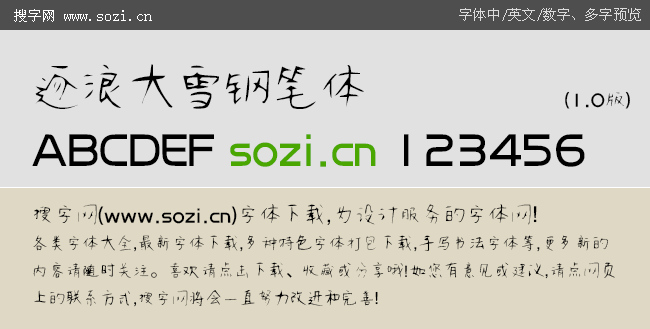
逐浪大雪鋼筆體
搜字網(wǎng)提供一款逐浪大雪鋼筆體中文書法字體下載,逐浪大雪鋼筆體是一款手寫風(fēng)格的鋼筆書法字體,字體書寫流暢,字形大方,整體效果十分出色,適合應(yīng)用于廣告設(shè)計(jì)、名片設(shè)計(jì)、包裝印刷、兒童產(chǎn)品設(shè)計(jì)等應(yīng)用。